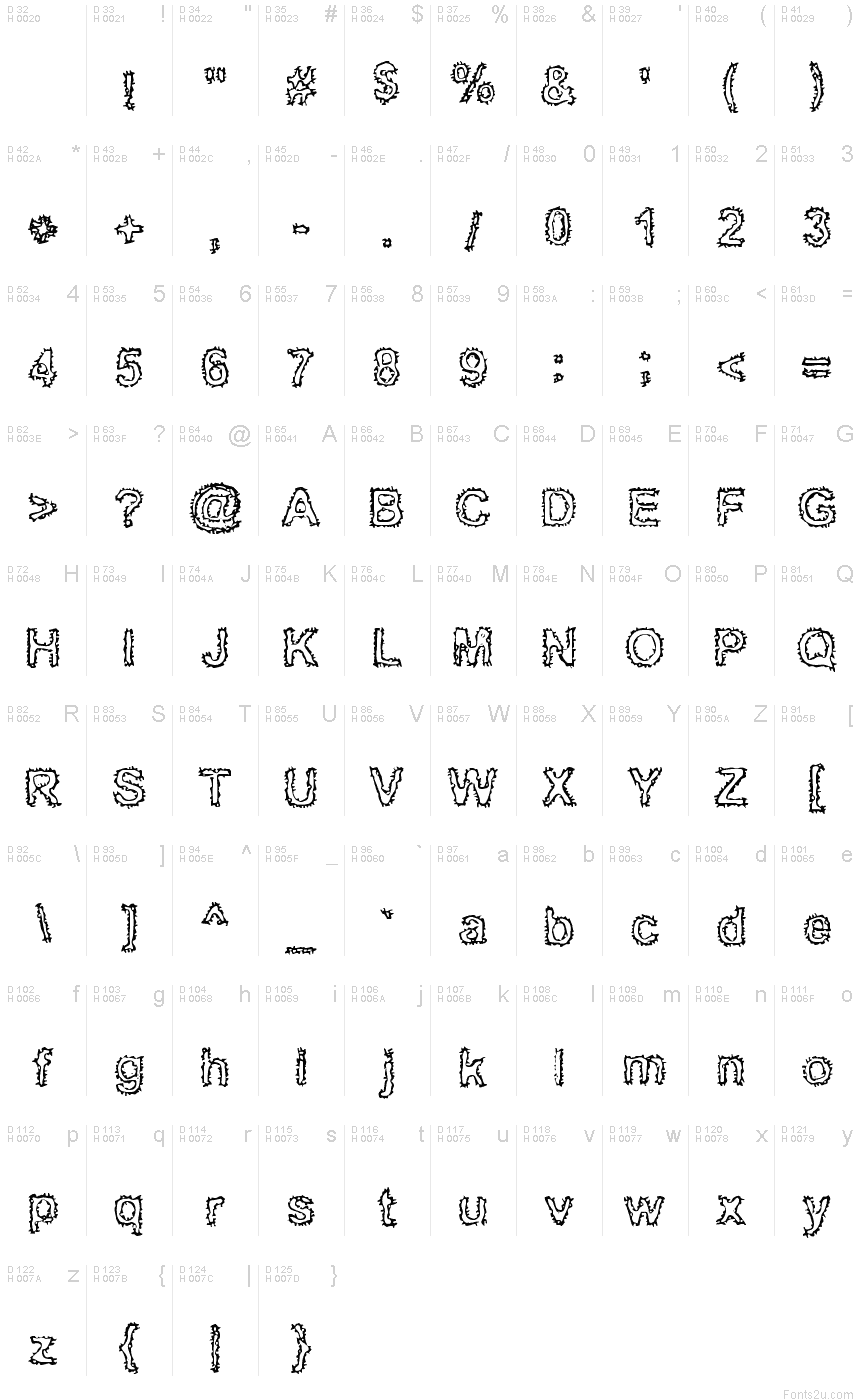
خط BN Kuktus من تصميم Ben Nathan هو خط مجاني ومعرض للتشويه، يبدو وكأنه نبت من الأشواك والحبر السائل. تبرز كل حرف بزوايا حادة وحواف غير منتظمة، مما يمنح الكلمات ملمساً خاماً مرسوماً باليد، يشبه في هيئته مزيجاً بين الصبار وكائن حي. تخلق الأشكال الملتوية والمتراصة إيقاعاً كثيفاً وحيوياً يجذب الانتباه فوراً على أي خلفية داكنة أو فوضوية.
مع خط BN Kuktus، يمكنك إضفاء طابع مرعب ومميز على ملصقات الرعب، ومنشورات الهالوين، ولافتات المنازل المسكونة، وأغلفة المجلات الفنية، وعناوين الألعاب، وتصاميم الحفلات تحت الأرض. يتألق هذا الخط المجاني عند استخدامه بأحجام كبيرة حيث تظل حوافه الشوكية واضحة ومقروءة؛ لذا ننصح بدمجه مع خط حديث وبسيط بلا زوائد (sans serif) للنصوص الأساسية للحفاظ على سهولة القراءة، بينما تترك العناوين تعبر عن جاموحها.